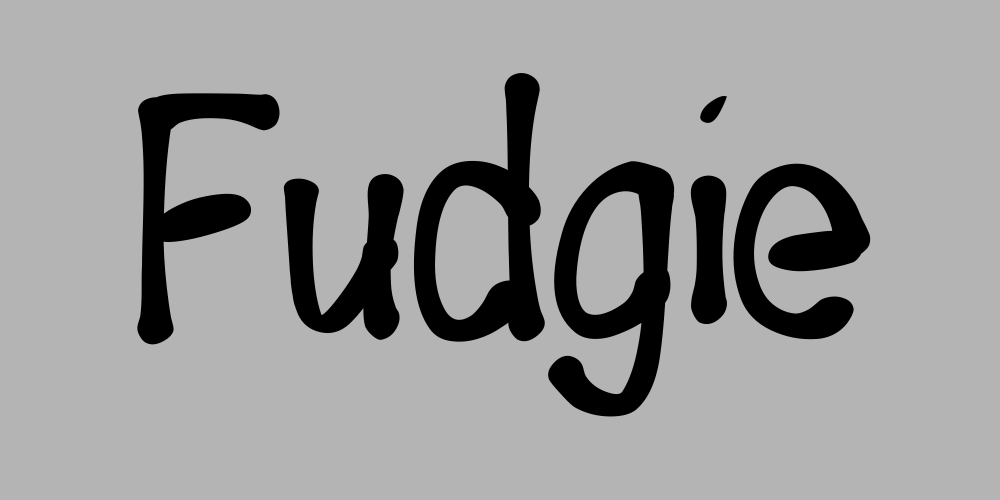
A fonte Fudgie é perfeita para quem busca algo leve e divertido no design dos seus projetos digitais. Desenhada pelo designer Hamilton, esta fonte está repleta de personalidade e encanta por sua aparência simples e descontraída, tornando-a perfeitamente adequada para aplicativos como logotipos ou cartões de aniversário. Com linhas elegantes e uma tipografia suave que combina harmoniosamente com qualquer tema, a Fudgie é um recurso gráfico ideal para quem busca algo leve e divertido sem perder o tom mais sofisticado. Seja você um criador de sites, designer de logotipos ou simplesmente um entusiasta do design digital, a fonte Fudgie certamente será uma escolha inteligente para tornar seus projetos ainda mais atraentes e personalizados.